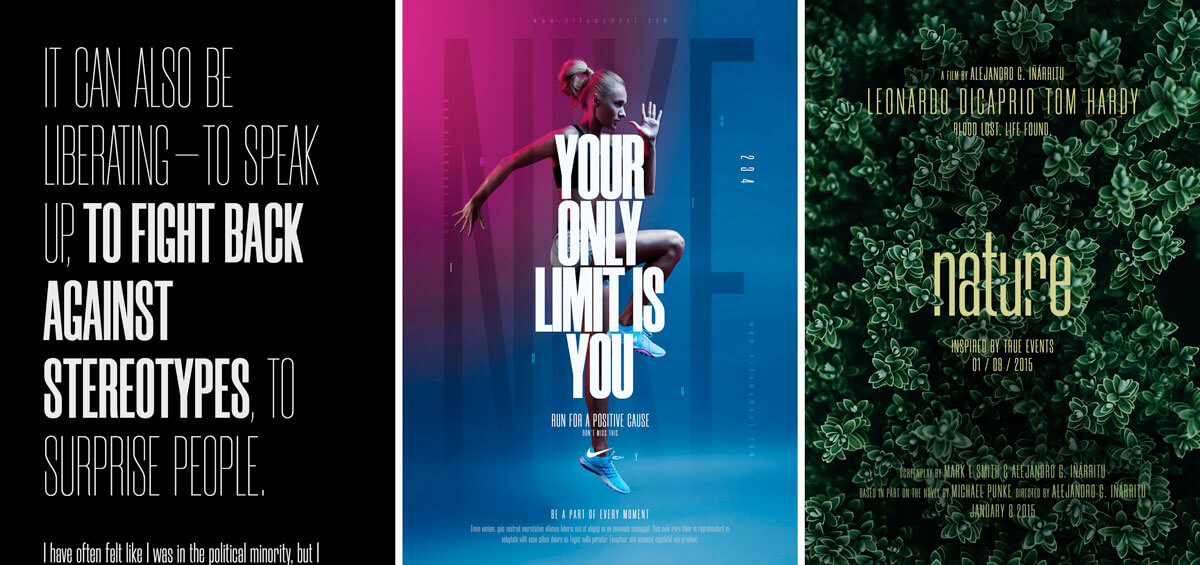
絶対に使いたくなる最先端フォント19選
毎年、新しいデザインのトレンドと今後数カ月間に使用するテクニックのリストが出てきます。しかし、タイポグラフィについてはどうでしょうか?
活字の傾向については多くの場合これらのリストの一部にふくまれていますが、あなたの生活を楽にするであろうフォントを紹介しているものは多くはありません。 Designmodoはその問題を解決するためにここにあります。ここでは、今年デザインプロジェクトで使用したい19のGo-Toフォントのリストをまとめました。
一目でわかる2019年型トレンド
今年のタイポグラフィに関して、すでに気づいていることがいくつかあります。このリストのオプションの多くは、これらのトレンドスタイルを念頭に置いています。
・サンセリフは、3〜5行のテキストでタイポグラフィを積み上げました。
・より多くのserifフォントオプションの使用
・古典的な雰囲気を持つレトロとアウトライン/インラインスタイル。
・細かい文章のために手の込んだスワッシュ。
・太い線と太字。
Coves
Covesは素敵な丸い形と大文字と小文字のフルセットを持つサンセリフフォントです。 丸みを帯びた縁がこのフォントに特別な感触を与えます。Behanceのデザイナーから無料で(個人使用に限ります)ダウンロードしてください。
Univers
Universは「昔ながらの、しかし良い」というフォントです。この書体はとても使い勝手がよく、ほとんどすべてのデザイン審美的なものに簡単に収まります。 このサンセリフのシンプルな形はまた、特大または積み重ねられたタイポグラフィにぴったりです。この高級フォントはMyFontsから入手可能です。
Morganite
Morganiteは驚くほど複雑なフリーサンセリフフォントです。 大文字の文字セットは表示に適しており、小文字の文字は「ぎくしゃくした」感じがしますが、短いテキスト要素にはうまく機能します。 そのような高いX高さを持つ書体の場合、それはかなり読みやすいです。 Behanceでデザイナーから見つけてください。
Lato
Latoは決して古くならないフォントの1つです。 半円形の文字の細部はLatoに暖かさの感覚を与えます、一方強い構造は安定性と真剣さを提供します。 男性と女性、真剣だがフレンドリー、というフォントです。
デザイナーのŁukaszDziedzicによると、「夏の気分で使ってほしい」。 これは、Googleフォントに含まれているため、一般的な書体です。
Evolve Sans
Evolve Sansには、複数のウェイトの10のフォントと、特定の文字や用途には楽しい未来的な代替フォントが含まれています。 シンバージョンは、特大のアプリケーションには十分な重さしかありませんが、通常の太字の太さは、ほとんどすべての表示テキストにとって例外的です。
Quick
Quickはエレガントで細い線のサンセリフです。 特大サイズや表示に使われるこのフォントは非常にインパクトがあります。 このフォントは多言語サポートを含み、フルキャラクタセットを含みます。 GraphicFreshからダウンロードしてください。
Mosk
Moskは、9つのスタイルとたくさんの太さを持つ強力なSans Serifフォントで、オールインワンのフォントソリューションです。 斜めの文字ときれいな線が積み重ね、本文、そして表示に最適です。 Behanceのデザイナーからダウンロードしてください。
Burgess
Burgessは、フルフォントファミリーの中にたくさんのオプションがある、とても読みやすいセリフです。 太字と半太字のバリエーションは表示が見栄えがよく、標準は小さいテキスト要素に最適です。 プレミアムフォントは、Colophon Foundryから入手できます。
GT Super
GT Superは、汎用性に富んだモダンスタイルのセリフです。 それは読みやすく、複数の重みで風通しがよく、理想的な万能ソリューションです。 (さらに、スクリーンと印刷物で美しく映ります。)
デザイナーから:GT Superは1970年代から80年代にかけてのディスプレイセリフ書体に対する広範な調査の結果です。 このプレミアムフォントは、Grillitypeから入手できます。
Playfair Display
Playfair Displayは、太いスタイルと細いスタイルの多目的セリフ書体です。 大きな文字には最適ですが、小さなサイズでも読みやすいです。 Google Fontsから無料で入手できます。
Giveny
Givenyは、すべて大文字の古典的なスタイルのセリフです。 特別なものを必要とするプロジェクトに正しい感触を追加するために表示用に使用してください。 Behanceのデザイナーからダウンロードしてください。
Monkstead
Monkstedは塗りつぶしてもアウトラインとしても使える楽しいレトロスタイルです。 それは5つのスタイルを持ち、ビンテージのロゴとポスターの静脈で作られています。 Dribbbleのデザイナーから無料版(ラウンドスタイル)を入手してください。
Circus Display
Circus Displayフォントは、レトロなスタイルと楽しいスワッシュとテールを備えた多目的フォントです。 あなたが面白い表示オプションを必要とするならば、これが最適かもしれません。 デザイナー曰く:このラフな書体は強いカリスマ性があり、観客を魅了します。
2つの異なるスタイル(通常とストライプの1つ)を持ち、「古さ」の程度を自由に編集することができます。PixelBuddhaからこの無料のフロントをダウンロードしてください。
Bobby Jones
Bobby Jonesは、丸みを帯びたスタイル、ラフで柔らかいオプション、およびアウトラインスタイルを備えた、楽しくファンキーなフォントです。 この書体は風変わりな性質を持っていますが、クールなレトロ感もあります。 PixelSurplusから無料でダウンロードしてください(個人使用のみ)。
Elephant
Elephantはエレガントなアウトラインスタイルのサンセリフで、画像や他のクリエイティブな素材と組み合わせることができます。 線は太くてさわやかで、デザインはシンプルでちょうど良い角度と重さで魅力的です。 無料でBehanceのデザイナーからそれをダウンロードしてください。
Puzzled
Puzzledは長い尾および精巧なラインが付いている流行の原稿であす。 フォントはより女性らしい雰囲気を持っていますが、それは多くのアプリケーションで使えます。 最も効果的な用途は、精巧なスタイルを最大限に活用するために、数文字の単純なテキスト要素を含めることです。 PixelSurplusから無料でダウンロードしてください。
Peace Sans
Peace Sansは大胆で目に優しいです。 フリーフォントは非常に用途が広く、高級に見えるデザインをしています。 グリフもサポートされています。 Behanceから無料でダウンロードしてください。
Wanderlust
Wanderlustは大胆で珍しいので、このテキストを表示すると魅力が増します。
デザイナー曰く:「ラウンドとエッジのあるスラブセリフの組み合わせにより、Wanderlustは景観や山の特徴、そして田舎の木造建築のハイキングからインスピレーションを得ているユニークなスタイルを持っています。」Behanceから無料でダウンロードしてください。
Adelle
Adelleはこのリストの中で最も用途の広いフォントの1つかもしれません。 (だからリストの最後にしました。)書体には太字の行が含まれており、多くの個性があります。
作成者曰く、「目立たない外観、優れた質感、そしてやや濃い色は、最も容赦のない用途でも、連続したテキストでも完璧に振る舞うことを可能にします。 活字が大きくなるにつれて、Adelleフォントは一連の測定された特殊性を通じて個性を示し、覚えやすく識別しやすくします。」